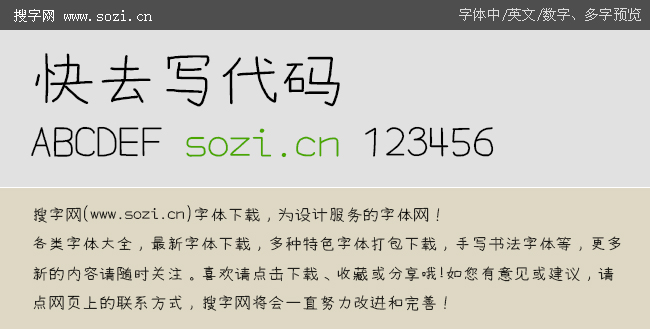
快去寫代碼字體
搜字網(wǎng)給大家提供一款快去寫代碼字體中文字體下載,快去寫代碼字體是一款完全用鼠標(biāo)構(gòu)建字形的“仿”手寫體,本字體最大的特點(diǎn)就是里面的絕大部分字形均由鼠標(biāo)繪制。適用于海報(bào)設(shè)計(jì)、包裝設(shè)計(jì)、廣告設(shè)計(jì)等場(chǎng)景。